Il 17 aprile 2025, Google ha distribuito la Beta 4 di Android 16 a tutti gli utenti iscritti al programma Beta in possesso di un dispositivo Pixel compatibile. L’aggiornamento non stravolge l’esperienza d’uso, ma introduce alcune interessanti rifiniture grafiche, tra cui un ritocco evidente all’orologio nella barra di stato.
Un piccolo grande dettaglio: il nuovo font dell’orologio
Chi ha un occhio attento (e magari un Pixel 9 tra le mani) noterà subito che i numeri dell’orologio in alto a sinistra sono leggermente cambiati. Google ha aggiornato il font, rendendo in particolare le cifre “1” e “2” più larghe, mentre lo “0” è diventato un po’ più stretto. Anche la spaziatura tra i numeri è stata ritoccata: ad esempio, il divario tra l’1 e il 2 risulta ora più ampio.
Tutto sembra un po’ più “arioso” e moderno, in linea con un generale processo di rinnovamento estetico che Google sta portando avanti già da tempo. Nessuna modifica invece per la parte destra della barra, dove rimane invariato il font per la percentuale della batteria e le altre icone.
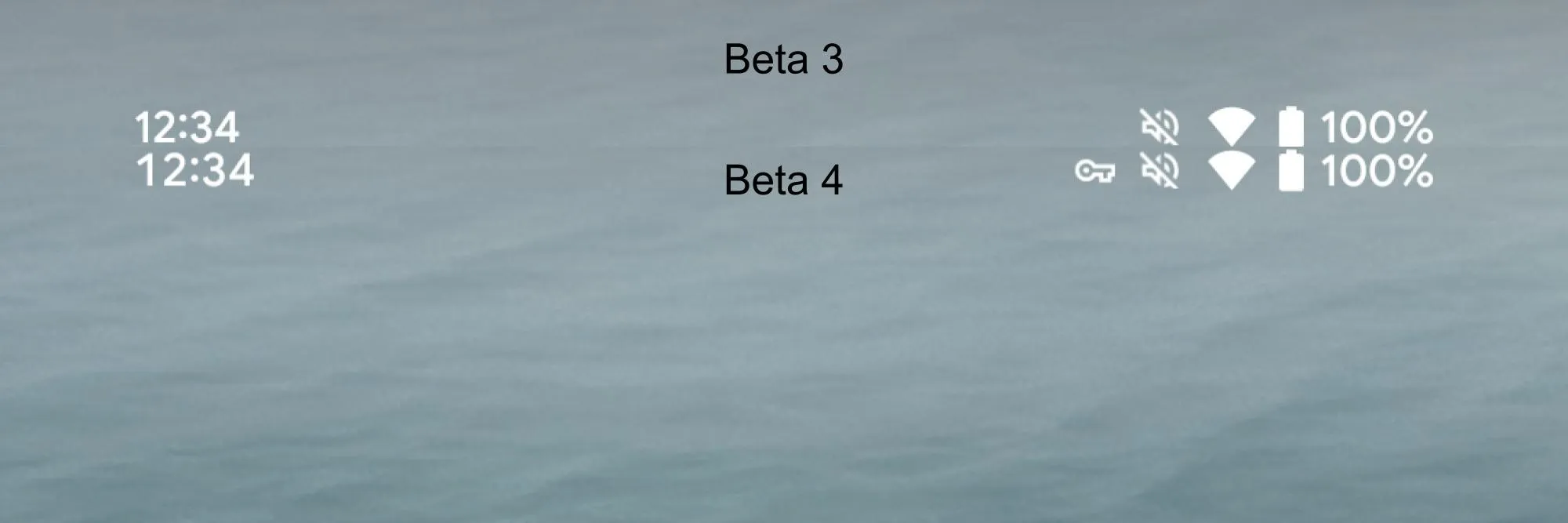
Chi ha già aggiornato probabilmente si è accorto subito del nuovo look dell’orologio, un cambiamento che, come spesso accade, colpisce all’inizio ma poi diventa parte integrante dell’interfaccia. Non è ancora chiaro se questa modifica arriverà anche nella versione stabile di Android 16, prevista per giugno, ma tutto lascia pensare che Google voglia continuare su questa strada.
Insomma, Android 16 continua a crescere passo dopo passo, e anche se si tratta di dettagli apparentemente minori, come il nuovo font per l’orologio, il risultato finale sarà un sistema sempre più curato e coerente.